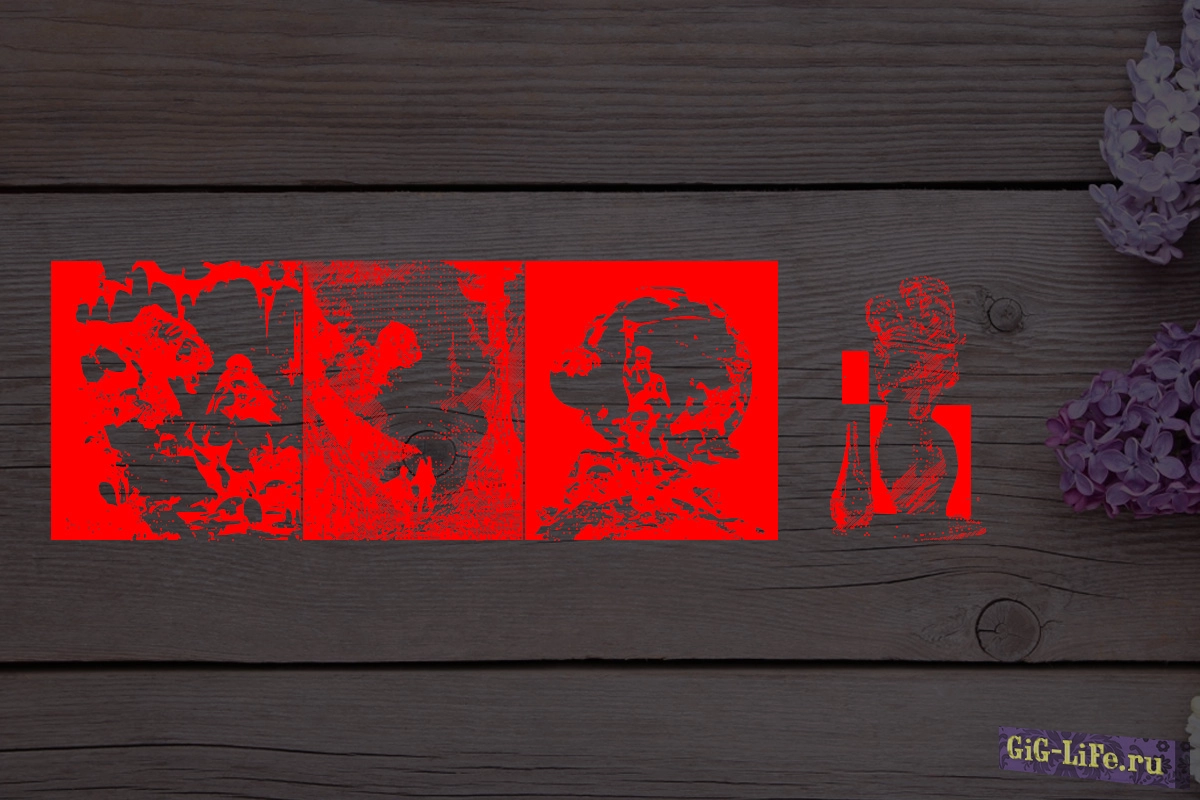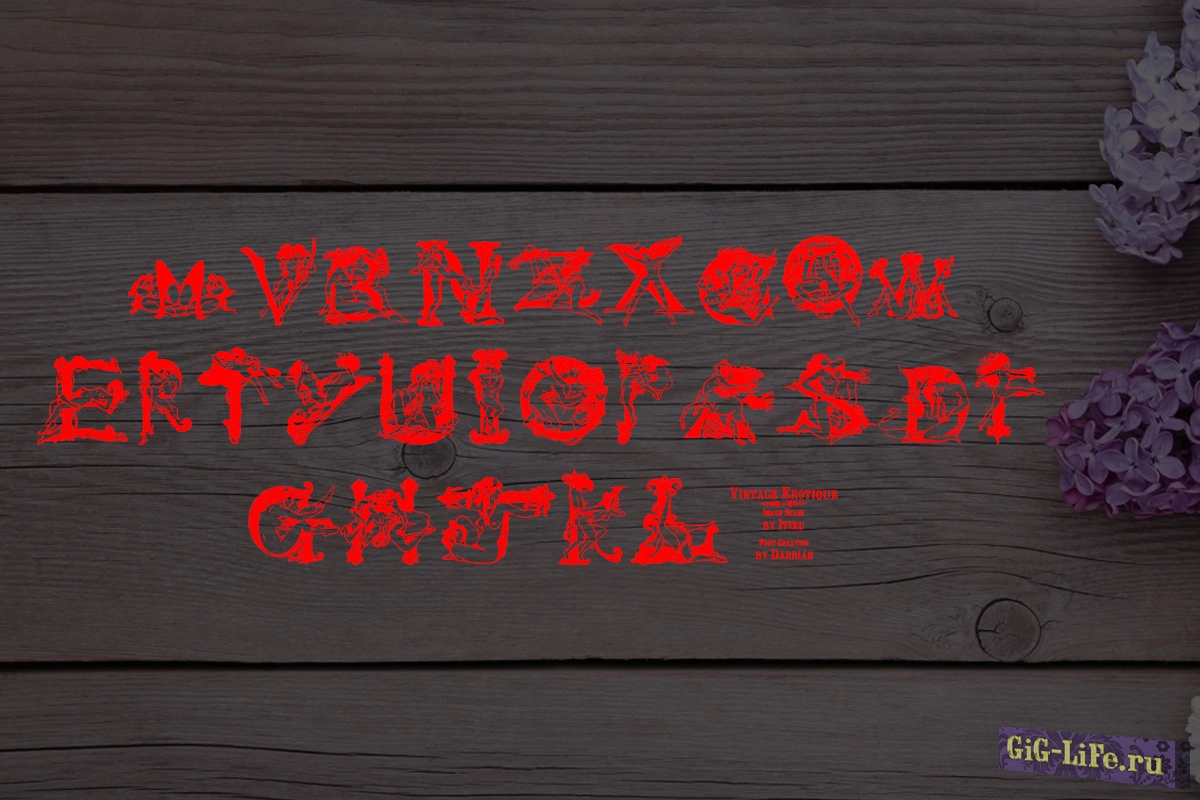
Vintage Erotique - это эротический шрифт, который создан специально для использования в программе Photoshop и других креативных проектах, построенный на уникальных символах.